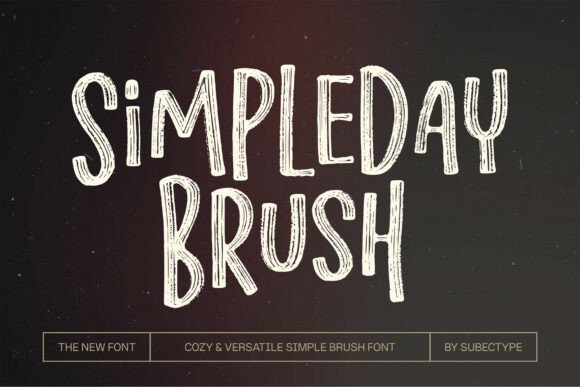
Simpleday Brush
適切なデザイン要素を見つけるのは難しい場合がありますが、Simpleday Brushは作品を即座に引き立てる優れたコレクションを提供します。
POD(オンデマンド印刷)製品、結婚式の招待状、またはソーシャルメディアのグラフィックを作成している場合でも、Simpleday Brushは理想的です。